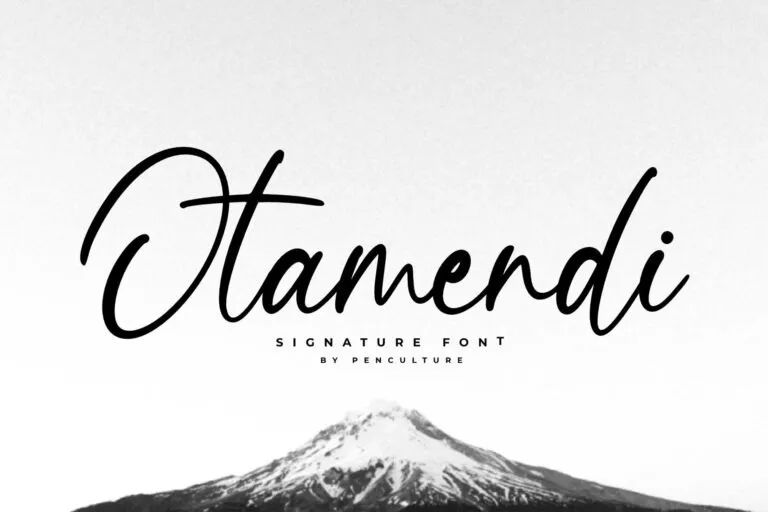
Otamendi Font – Download Grátis
A fonte Otamendi é um estilo elegante e altamente sofisticado, criada pela Pen Culture, especialmente projetada para marcas de marca que valorizam uma fidelidade genuína à escrita a mão. Esse script está idealmente concebido para empresas que procuram uma tipografia de texto bold com um toque autêntico e vívido da escrita a mão. Otamendi oferece aos designers uma opção perfeita para criar marcas elegantes, chamativos e autênticos sem perder o brilho sofisticado presente nas linhas da fonte. Ideal tanto para aplicar em nomes de marca quanto no design de materiais publicitários ou qualquer outro trabalho onde um toque delicadamente elaborado seja desejável. Para quem busca uma tipografia que combine estilo e simplicidade, Otamendi é certamente o caminho a seguir.